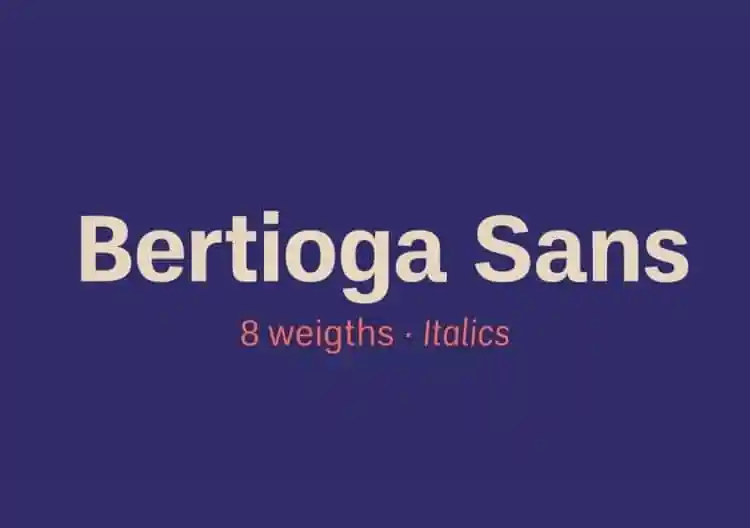
Bertioga Sans Serif Font Family – Download Grátis
Bertioga Sans Serif é uma fonte séria que oferece estabilidade constante com sua elegância moderna. Lançada originalmente em 2020, após a pausa de mais de dez anos no desenvolvimento das famosas fonts do UnB Pro, essa nova font foi criada como um continuidade desta série. Com linhas retas e generosas, Bertioga Sans Serif é perfeitamente adequada para aplicativos que exigem uma estabilidade visual consistente. Seja em rótulos de produtos ou gráficos de websites, a Bertioga Sans Serif oferece um equilíbrio entre modernidade e resistência, sendo especialmente ideal para ambientes digitais. Esta fonte do designer 99designs é perfeita para qualquer projeto que valoriza uma aparência limpa e segura em seu design gráfico.